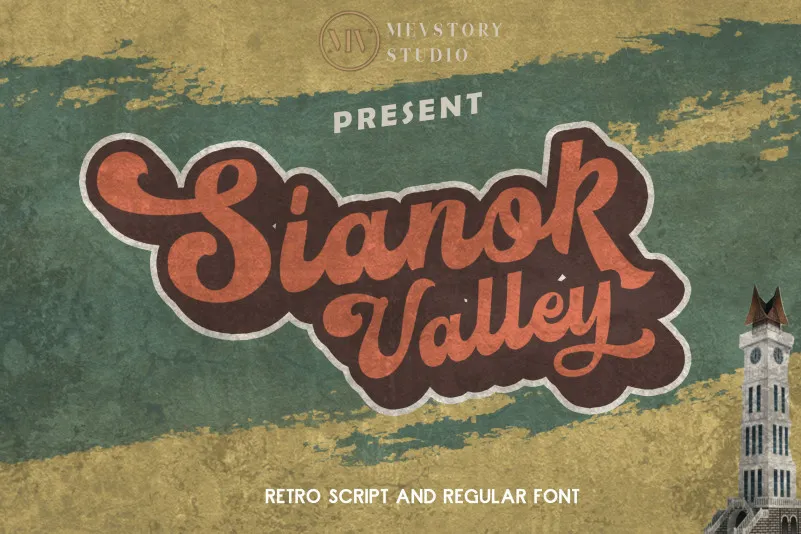
Sianok Valley Retro Font – Download Grátis
Sianok Valley Retro Font é uma família de fontes que remete-nos à estética dos serifos modernamente revigorada, perfeita para criar um ar nostálgico em seus designs. Seu contraste leve e sua simplicidade marcante, combinado com formas quadradas de caracteres redondos, resultam numa tipografia suave e reconfortante que transmite uma sensação de confiabilidade e eficiência. Para designers que buscam um toque único em suas criações, essa fonte oferece variáveis significativas para personalizar cada projeto. Equil é particularmente aconselhado como uma opção ideal para logotipos, subtítulos (ou headlines), marcas de marca e outros elementos gráficos. Sianok Valley Retro Font se destaca por sua capacidade de trazer um toque retro e autêntico à designografia atual.
Designer: mhdafifersya